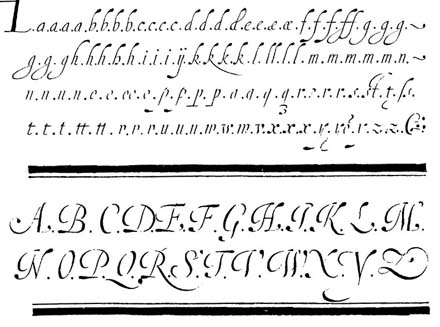
Martin Billingsley (1591-)Mestre-calígrafo do Maneirismo.Martin Billingsley introduziu a sua memorável obra The pens excellencie, or the secretaries delighte em 1618. A obra contém apenas 25 páginas de texto impresso, estas envolvendo 20 páginas com xilogravuras que mostram as diversas writing-hands, incluindo caligrafias do alfabeto grego e do hebreu. Martin Billingsley não delegava a execução das gravuras a terceiros, como o faziam outros autores, e teve todo o brio em executar as suas próprias gravuras. E afirmava com grande orgulho jamais ter copiado: «This is my Glory, That I haue not plaid the Theefe with any man, (though it were in my power to haue done it), But quicquid scripsi, scripsi: whatsoeuer I haue written, I haue done it my selfe.» Nos seus comentários sobre a antiguidade, a excelência e a diversidade, Billingsley define, seguindo as convenções da época, os seguintes estilos caligráficos: Secretary, Bastard Secretary, Roman, Italian, Court e a Chancery.
O livro indica também como afiar penas de ave e o modo correcto de segurá-las. Para o pragmático Billingsley, a arte de escrever era uma arte simples; devia aprender-se e aperfeiçoar-se não tanto através de complicadas construções geométricas, mas por simples emulação. Uma arte que um mestre passava aos seus discípulos, tida em grande estima, mas também funcional e prática, para ser aplicada em qualquer ocasião, em qualquer tipo de documento.